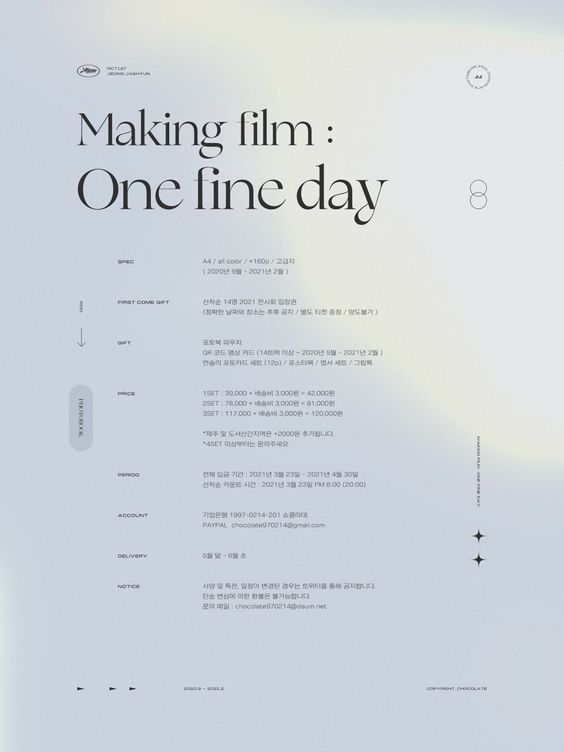
이 폰트는 뭘까요
One fine day 이 글자 보면
묘하게 흘림체가 있는 특이한 글자인데 모르겠네요 ㅠㅠ
특히 y자를 보면 끝부분이 특이하게 꼬리가 휘었는데 y자가 이렇게 나오는 폰트는 뭘까요 못찾겠네요
묘하게 흘림체가 있는 특이한 글자인데 모르겠네요 ㅠㅠ
특히 y자를 보면 끝부분이 특이하게 꼬리가 휘었는데 y자가 이렇게 나오는 폰트는 뭘까요 못찾겠네요
'Voyage'라는 폰트와 비슷한 것 같은데, 완전 똑같지는 않네요 ㅠ https://vj-type.com/6-voyage